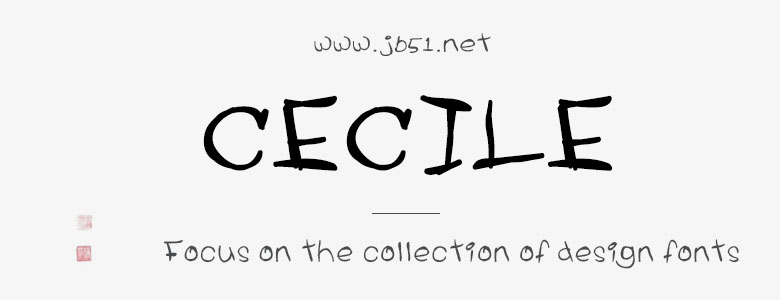
Cecile英文手寫字體,字體筆觸略細(xì),書(shū)寫流暢,略顯可愛(ài),具有很好的視覺(jué)感,適合應(yīng)用于藝術(shù)設(shè)計(jì)、平面宣傳設(shè)計(jì)、網(wǎng)頁(yè)設(shè)計(jì),書(shū)法字帖等領(lǐng)域。有需要的朋友快來(lái)本站下載使用吧。